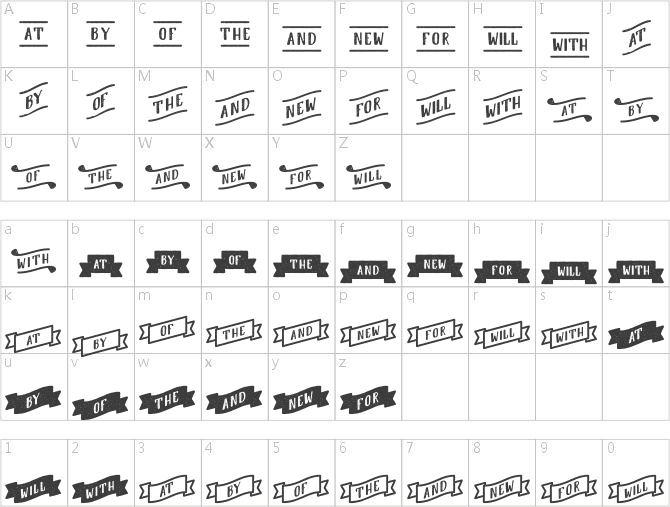
DrusticDialy-CatchWord 詳情頁
DrusticDialy-CatchWord字體字庫是一款讓人賞心悅目、百看不厭的英文字體,適合各類廣告和產(chǎn)品包裝設(shè)計應(yīng)用,字體大小0.31MB,格式為otf字體,上傳用戶是翰池書法,作者/版權(quán)方為未知